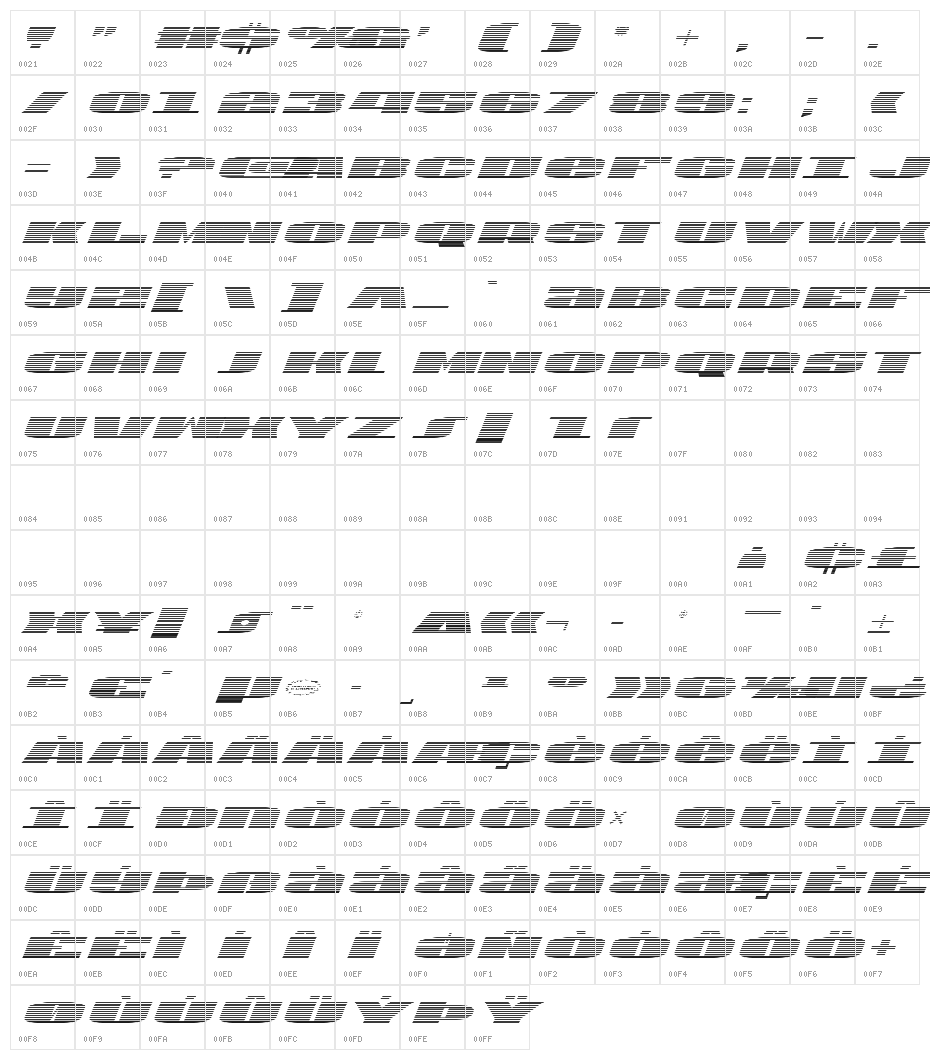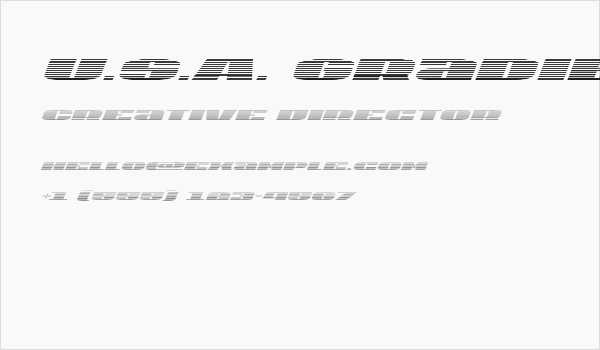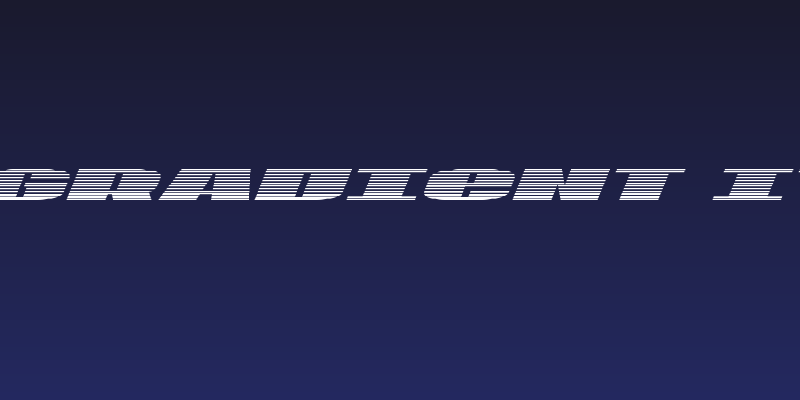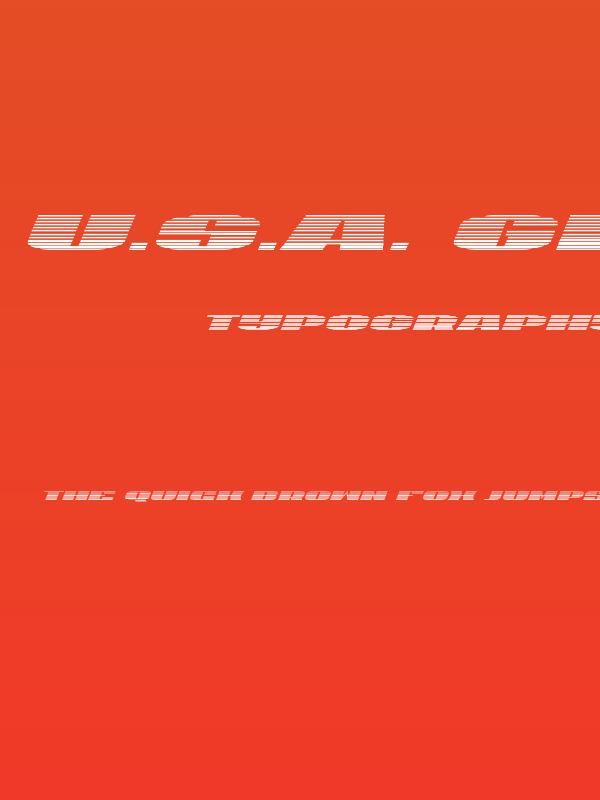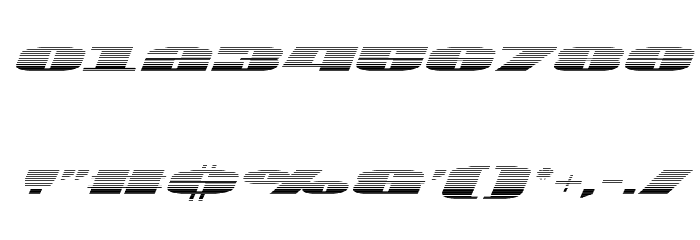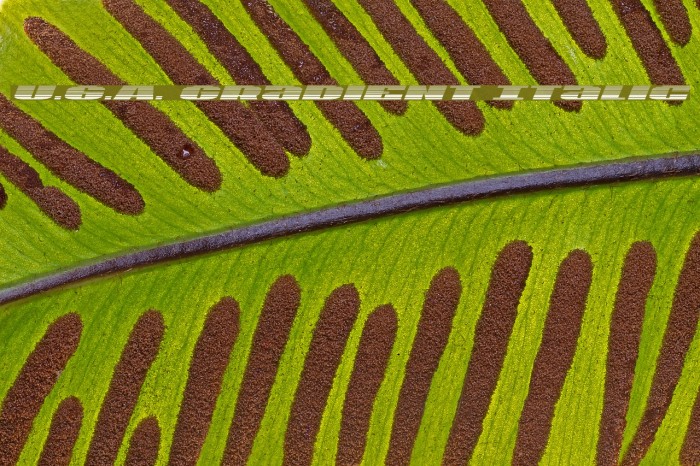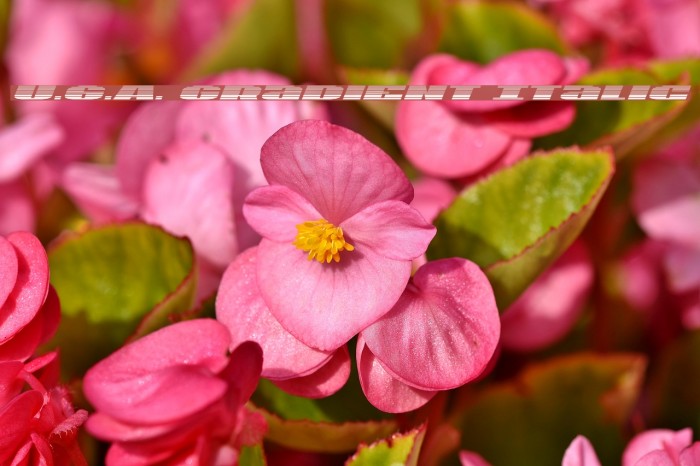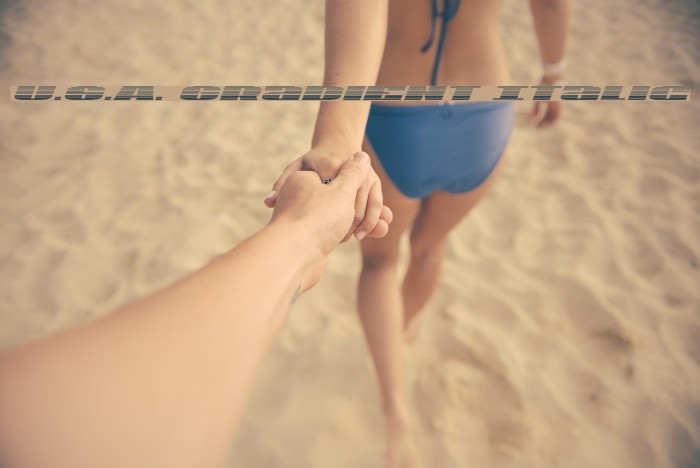
U.S.A. Gradient Italic Font
| Caso de uso | Logos, Headlines, Advertising |
| Proyectos propuestos | Ideal for projects requiring a futuristic or tech-oriented theme, such as branding for technology companies, sports team logos, or dynamic advertising campaigns. |